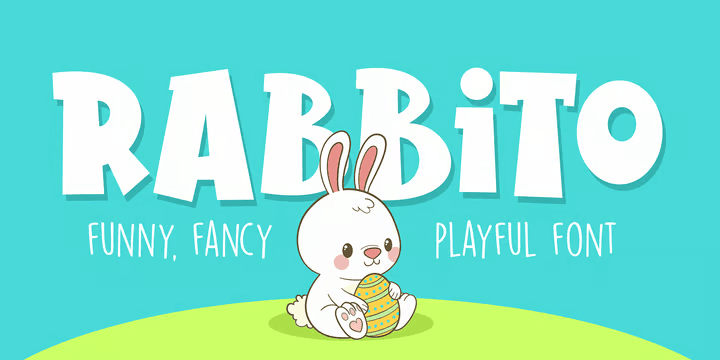
Rabbito
本日は『ピーター・ラビット』の作者、ビアトリクス・ポター Helen Beatrix Potter の誕生日(1866)なのでこちら。太めのポップなサンセリフディスプレイ。太さも傾きもてんでバラバラのストロークでラフにデザインされたディスプレイで、ちょっとしたセリフが統一感を出しているだろうか。全体的な雰囲気は子どもっぽくファンシーなので、お菓子やおもちゃなどに使えるだろう。イラストは明らかにジャパニーズカワイイの影響が見て取れる(笑)。大文字のみでアクセント記号もなく字種は最低限。